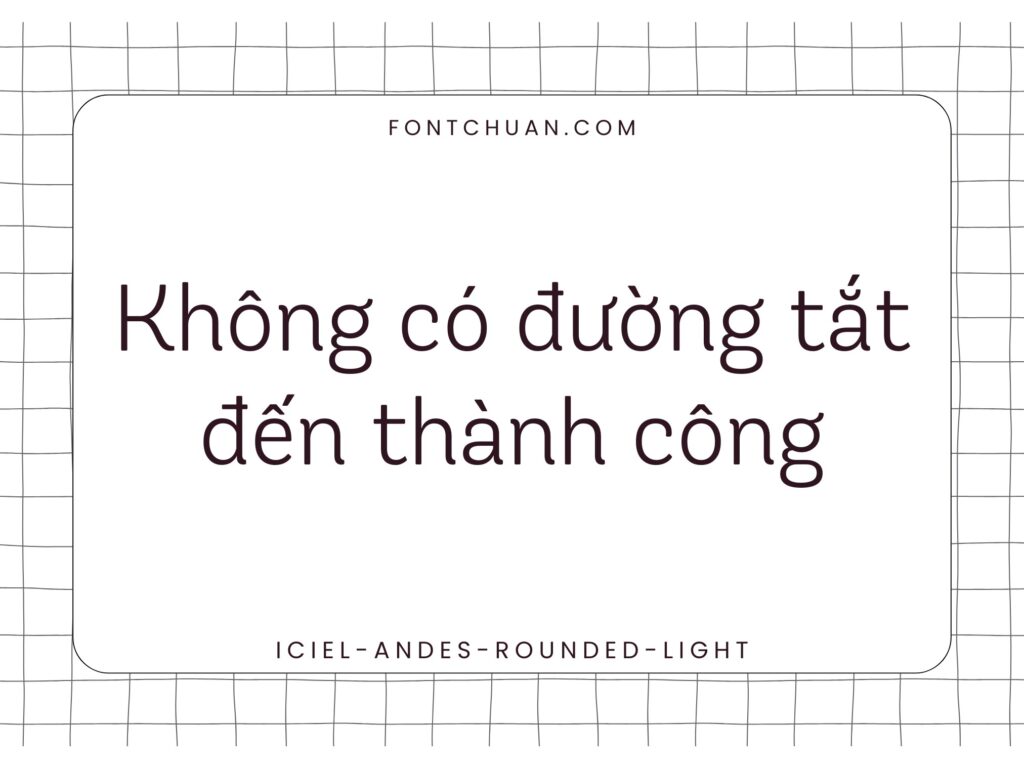
Font iCiel Andes Rounded Light Việt Hóa
Andes Rounded Light là một font chữ sans-serif hiện đại với các góc bo tròn mềm mại, mang lại cảm giác thân thiện và dễ tiếp cận. Được thiết kế bởi Daniel Hernández, font này thuộc họ Andes Rounded, nổi bật với các đặc điểm neo-humanist và đa dạng về trọng lượng. Để hỗ trợ cộng đồng thiết kế Việt Nam, Iciel đã Việt hóa font Andes Rounded Light, giúp font này hỗ trợ đầy đủ tiếng Việt cùng hơn 200 ngôn ngữ khác. Phiên bản Andes Rounded Light Việt hóa đã được thành viên Font Chuẩn sưu tầm và đăng tải, mang đến sự lựa chọn phong phú cho các nhà thiết kế.
Về đặc điểm thiết kế, Andes Rounded Light sở hữu các đường nét thanh mảnh với độ tương phản thấp, tạo nên sự thanh lịch và hiện đại. Font này rất phù hợp cho các thiết kế như tiêu đề, logo, tạp chí, sách và các dự án cần sự rõ ràng và tinh tế. Ngoài ra, Andes Rounded Light cũng là lựa chọn lý tưởng cho các ngành nghề như quảng cáo, giáo dục, công nghệ và bất động sản, mang lại phong cách chuyên nghiệp và thân thiện. Font này cũng thích hợp để sử dụng trong các sự kiện như Lễ hội, Sinh nhật và các dịp đặc biệt khác.